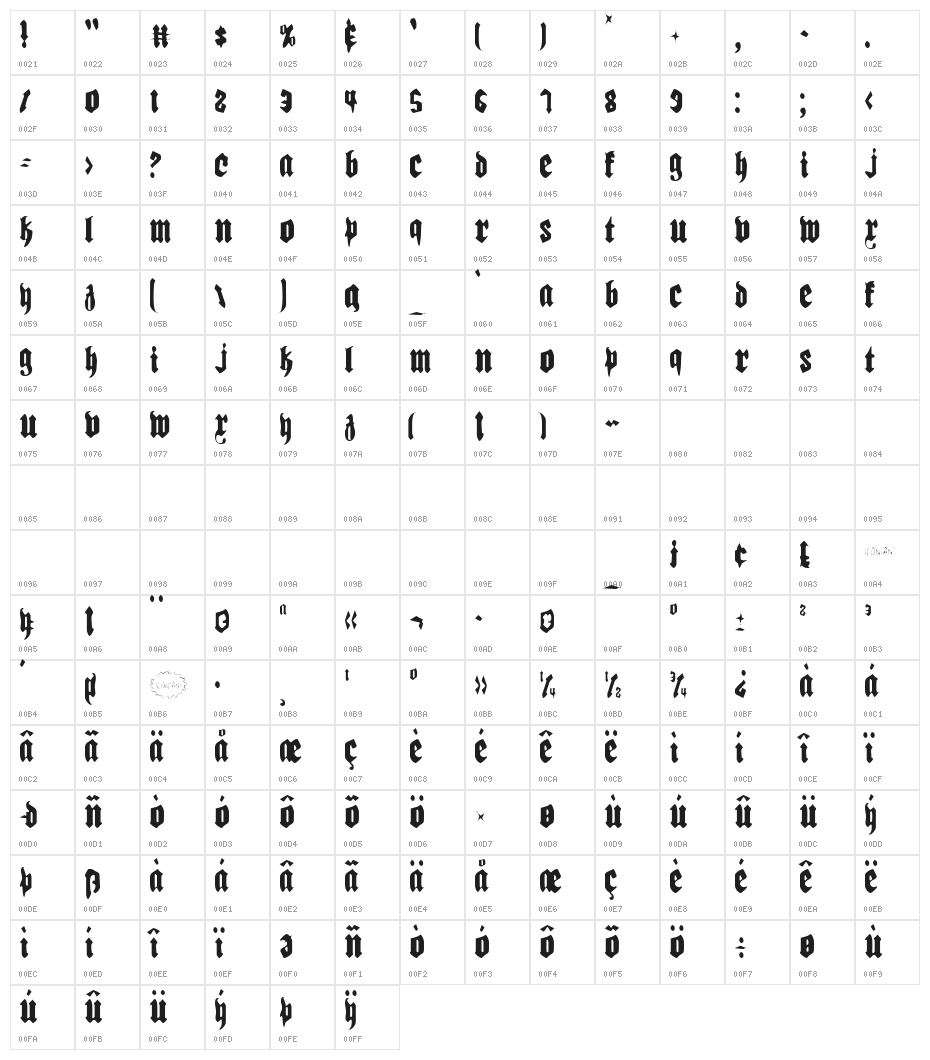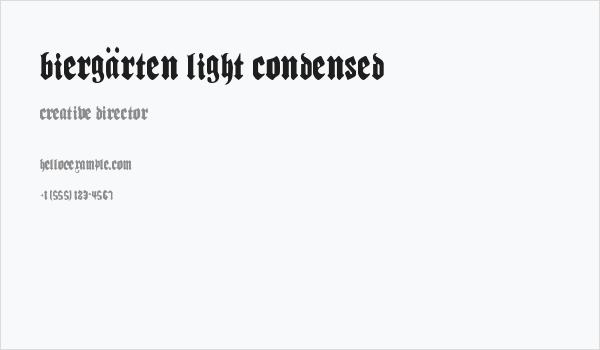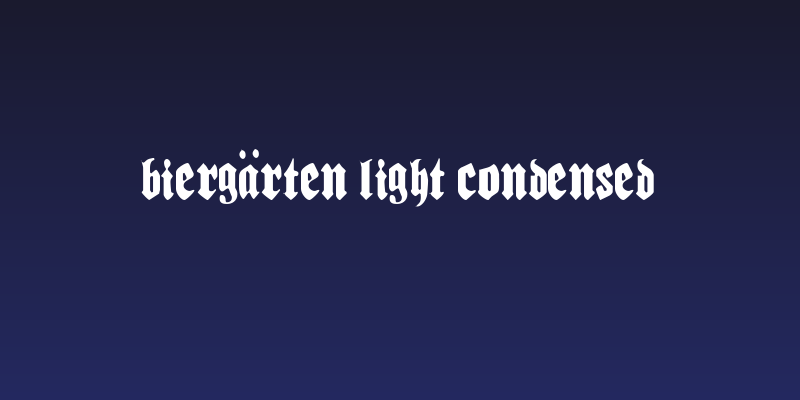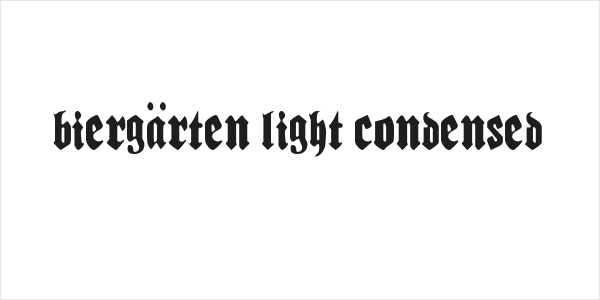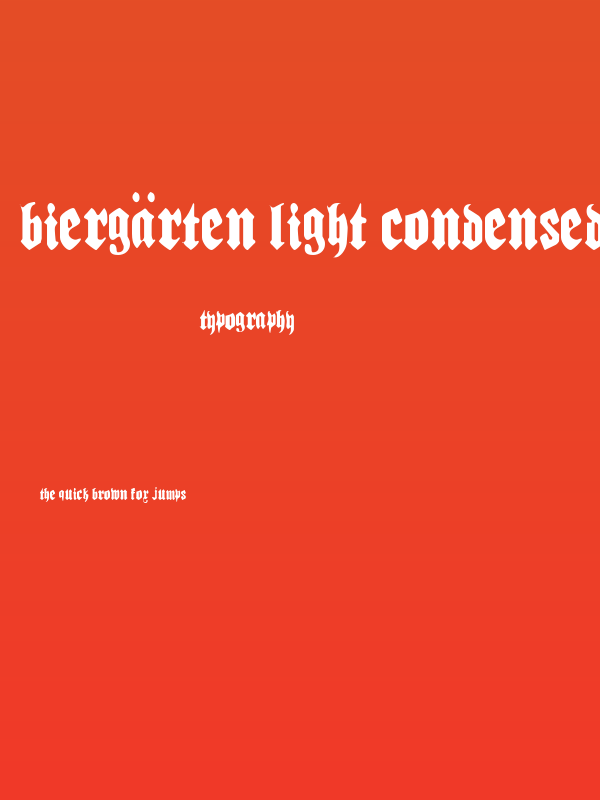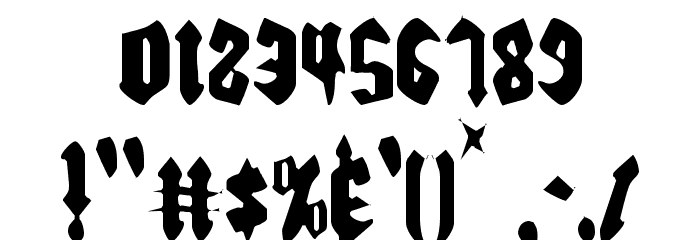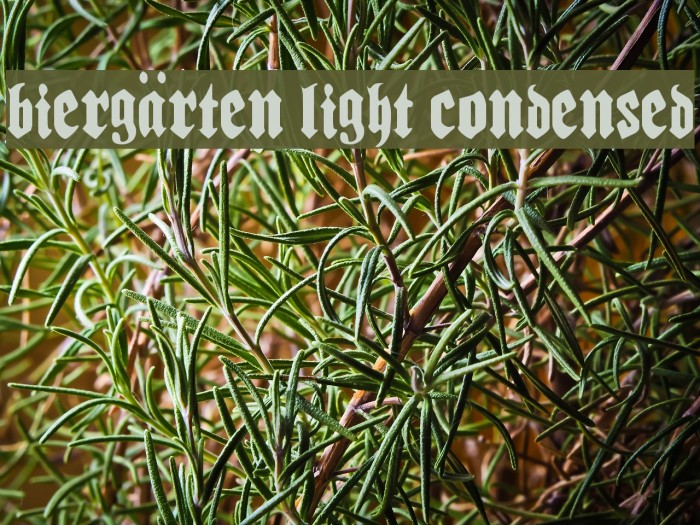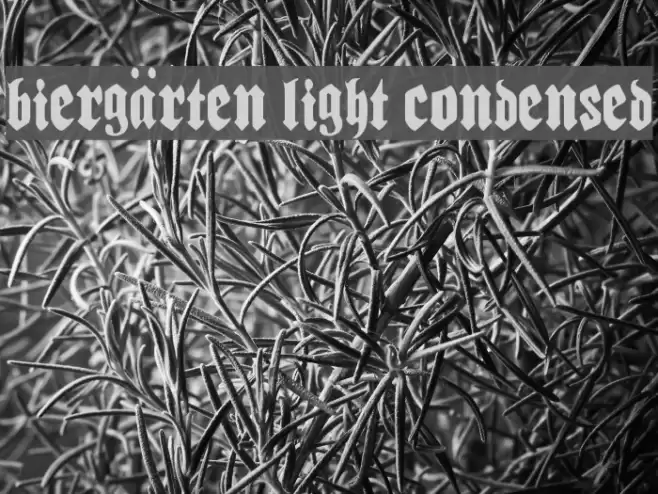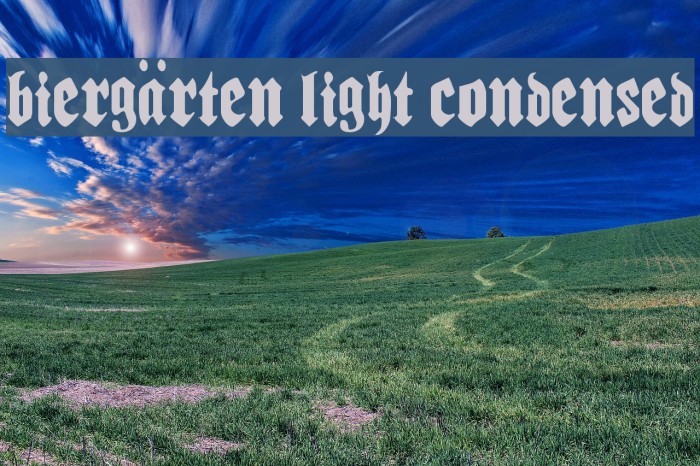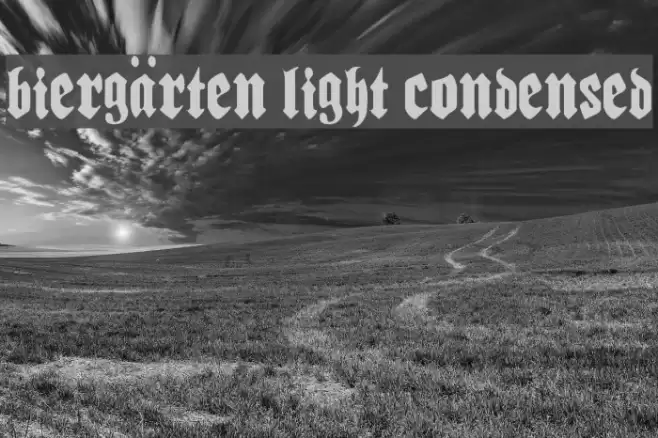
Biergärten Light Condensed Font
✎ Gothic
| नाम | Biergärten Light Condensed |
| वजन | Light Condensed |
| श्रेणियाँ | Gothic |
| चौड़ाई | Condensed |
| कंट्रास्ट | High |
| समग्र शैली | Vintage |
| उपयोग का मामला | Logos, Headlines, Decorative text |
| सुझाए गए प्रोजेक्ट | Ideal for projects requiring a historic or formal touch, such as certificates, invitations, or branding for traditional products. |